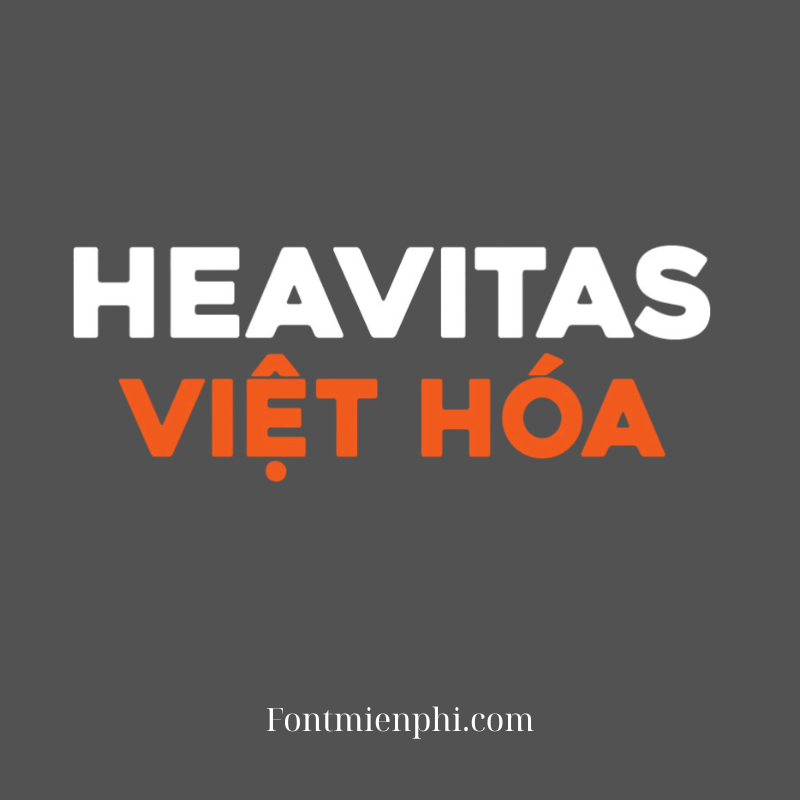
Font Việt hóa 1FTV Heavitas
Trong thế giới đồ họa hiện nay, việc lựa chọn một Font Miễn Phí chất lượng đóng vai trò then chốt giúp thông điệp truyền tải rõ ràng hơn. Font Việt hóa 1FTV Heavitas là một trong những lựa chọn hàng đầu cho những ai yêu thích phong cách mạnh mẽ và hiện đại. Với đường nét dày dặn, hình khối chắc chắn, bộ phông chữ này đặc biệt phù hợp cho các bạn học sinh, sinh viên khi làm bài thuyết trình hoặc thiết kế báo tường số. Sự rõ ràng của từng ký tự giúp người xem dễ dàng tiếp nhận thông tin ngay từ cái nhìn đầu tiên.
Đặc điểm nổi bật của bộ Font Việt hóa 1FTV Heavitas
Bộ chữ này nổi tiếng nhờ phong cách Sans Serif không chân, mang lại cảm giác tối giản nhưng vô cùng quyền lực. Khi sử dụng Font Việt hóa 1FTV Heavitas, bạn sẽ thấy sự cân bằng tuyệt vời giữa các khoảng cách chữ, giúp văn bản không bị rối mắt. Đặc biệt, phiên bản 1FTV đã được tinh chỉnh kỹ lưỡng để hỗ trợ đầy đủ hệ thống dấu tiếng Việt, loại lỗi hiển thị phổ biến khi dùng phông chữ nước ngoài.
Ứng dụng thực tế trong học tập và sáng tạo
Các bạn có thể ứng dụng bộ phông này vào việc thiết kế tiêu đề bìa sách, làm logo câu lạc bộ hay tạo các banner sự kiện tại trường học. Nhờ tính linh hoạt, nó không chỉ xuất hiện trên các ấn phẩm in ấn mà còn hiển thị sắc nét trên màn hình máy tính và điện thoại. Việc kết hợp 1FTV Heavitas với các phông chữ mảnh hơn sẽ tạo ra sự tương phản thú vị cho tác phẩm của bạn.